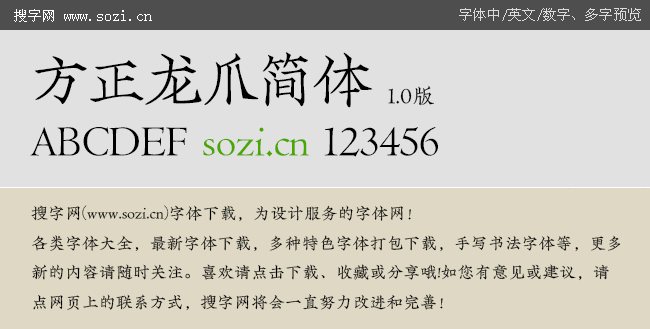
方正龍爪簡體
搜字網(wǎng)給大家提供一款方正龍爪簡體中文字體下載。方正龍爪簡體是在欣喜堂的授權(quán)下,方正電子根據(jù)日文同款字體基礎(chǔ)上修改,統(tǒng)一調(diào)整單字的布白與字面大小,并按照國家有關(guān)標(biāo)準(zhǔn)規(guī)范筆形,重新調(diào)整了字形結(jié)構(gòu),設(shè)計(jì)補(bǔ)足了簡體字,以滿足字庫產(chǎn)品化規(guī)格要求。此款字體適用于文字排版、廣告設(shè)計(jì)、海報(bào)設(shè)計(jì)等視覺環(huán)境。